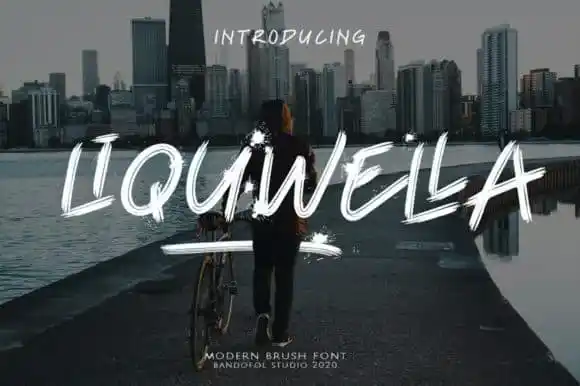
Liquwella Brush Font – Download Grátis
Liquwella Brush Font é uma fonte de estilo brush especial para design de destaque, projetada com paixão por designers digitais. Essa elegante e poderosa tipografia está repleta de atitude agressiva, criada com a ajuda de um caneto de pincel. Através da combinação única e interessante dessa fonte escrita à mão, você pode trazer um toque assertivo para qualquer projeto gráfico. Liquwella Brush Font é perfeita para inspirar suas criações em direção a algo forte e agressivo. Ela oferece uma versatilidade impressionante que certamente irá tornar seus projetos ainda mais destemidos e inovadores. Aqui está uma fonte de estilos únicos, ideal para quem busca deixar sua marca digital ainda mais poderosa e autêntica. Não perca essa oportunidade para explorar a criatividade com Liquwella Brush Font.